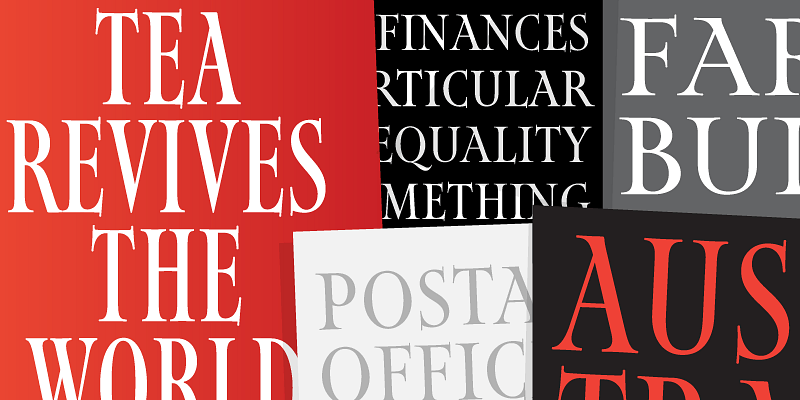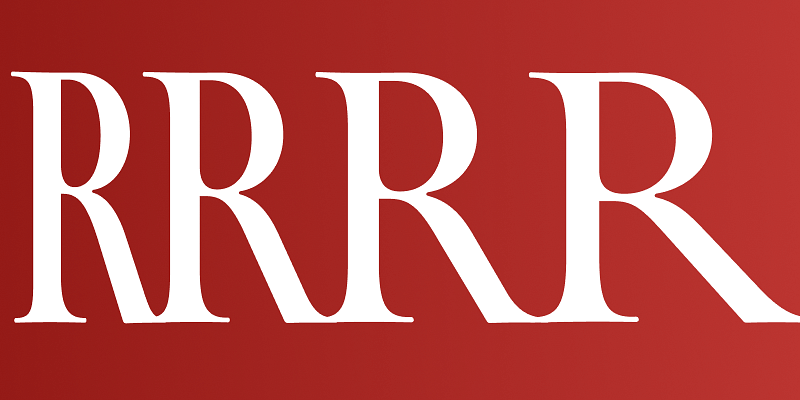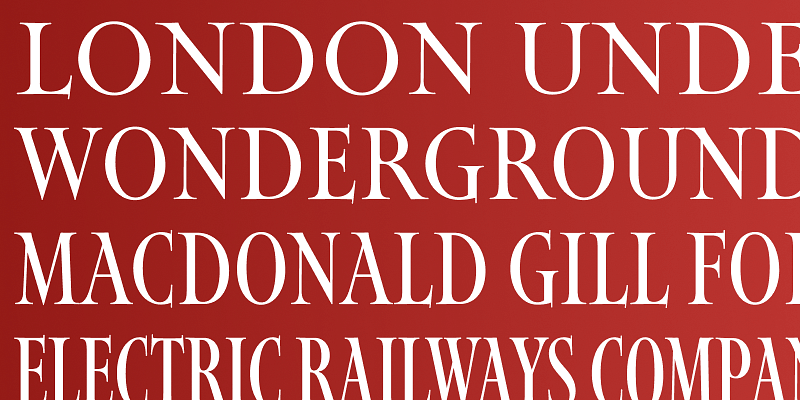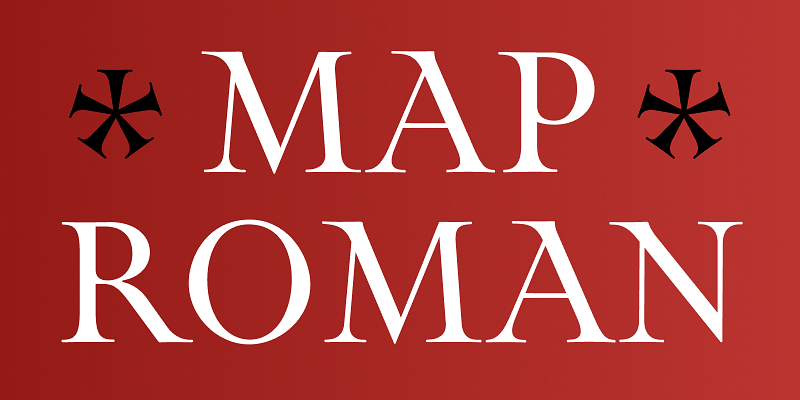
Map Roman è un elegante insieme di maiuscole da titoli, basato sulle lettere di MacDonald “Max” Gill, il cui lavoro includeva una varietà di mappe meravigliosamente curate di Londra, del Regno Unito e del mondo. Dopo essersi imbattuto nel suo lavoro in un museo di cartografia, DJR si è cimentato in un’interpretazione tipografica del suo stile che tenta di catturare la vivacità e l’autorità delle forme delle sue lettere. Map Roman si distingue per la sua flessibilità: nella sua parte più ampia è vasto e rigoglioso, mentre le sue larghezze più strette conservano il loro fascino anche se si stipano negli spazi più ristretti.